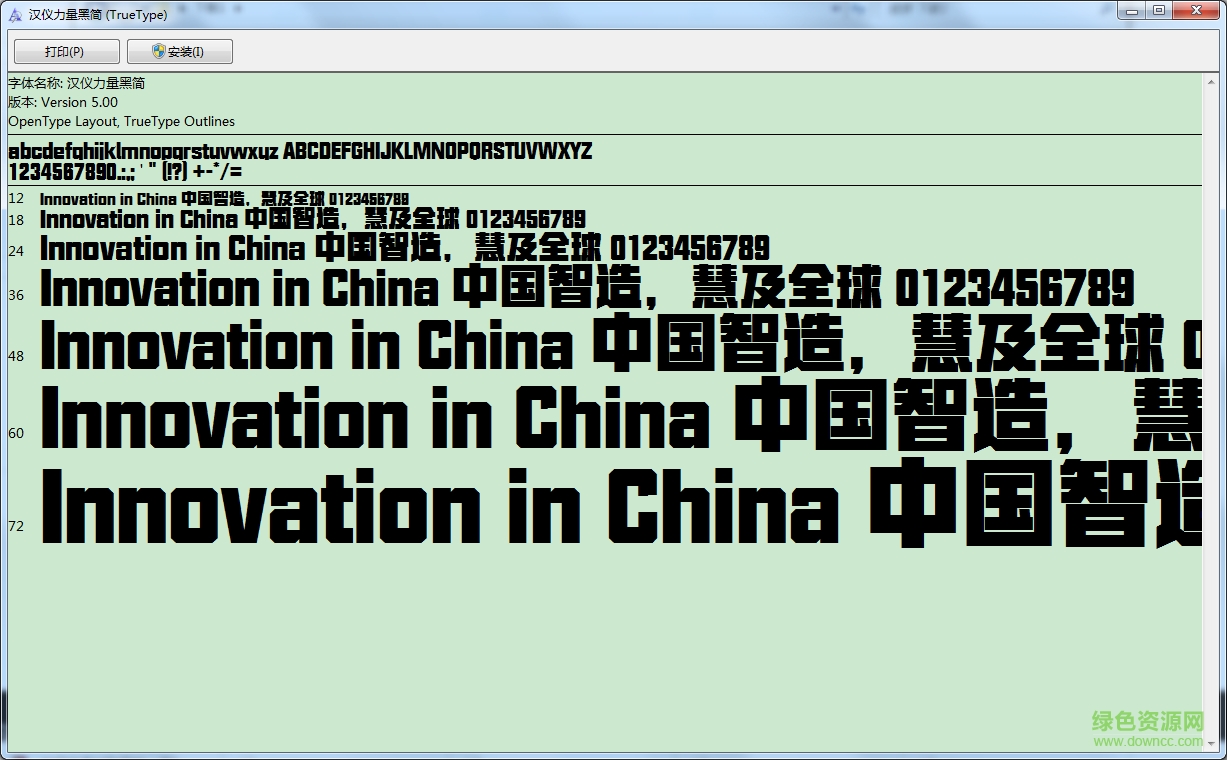
hyliliangheij是比較常用的英文字體,此款字體結(jié)構(gòu)簡(jiǎn)潔,易讀性強(qiáng),擁有較為完整的詞庫(kù),提供英文與數(shù)字輸入轉(zhuǎn)發(fā),安裝方法簡(jiǎn)單,廣泛的適用于各行各業(yè),喜歡的朋友歡迎來綠色資源網(wǎng)下載!